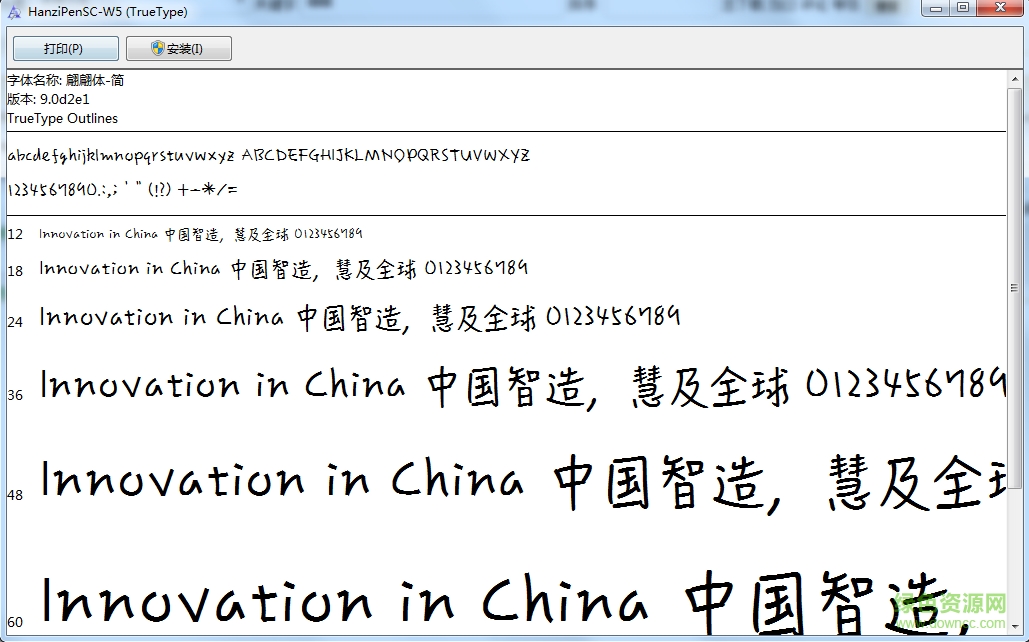
華康翩翩體是一款字跡娟秀干凈的華康字體,鋼筆手寫體風格,讓你的文字顯得更加隨性活潑,無論是文字記錄還是手賬日記都很適合的一款藝術字體,快來綠色資源網免費領取吧!
華康翩翩體是一款硬筆風格的書法字體,字呈長型,右上揚起,清秀灑脫,筆觸帶著俏皮的律動感,整體活潑生動,呈現自然手感,是一套親和隨興的手寫字體。適用于海報設計、包裝設計、網頁設計等廣告設計場合。
華康翩翩體完整不缺字,使用較為廣泛的華康字體,手寫書法的藝術韻味,讓您的閱讀更為舒適,商業(yè)使用還請去相關網站授權!